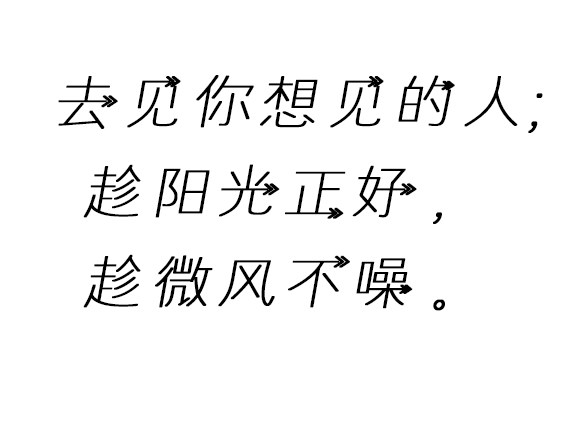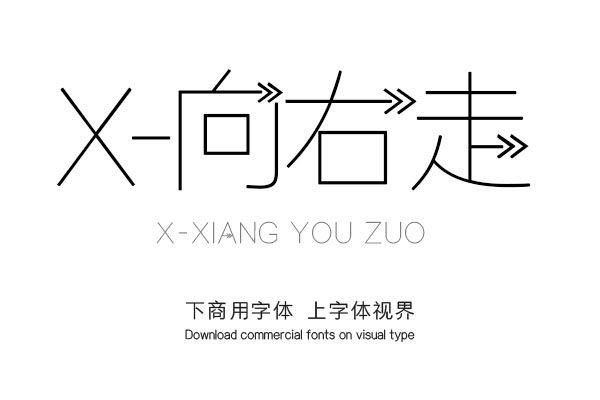
X-向右走——给自己一个方向
来一场说走就走的旅行,去见你想见的人。趁阳光正好,趁微风不噪;可是该往哪儿走呢?和我们一起向右走吧!
X-向右走
字形特点:
这是一款比较富有创意的手写体,我们在设计这款字体是,首先想到的是我的方向,由我自己主张。
该字体无笔画修饰但有笔画质感,笔画质感又是其灵魂。《X-向右走》的架构以拙示巧,线条质感与张力将其字体美表现的淋漓尽致,向右的箭头合理的嵌入字体中,使得字体不再枯燥更有趣味。
X-向右走